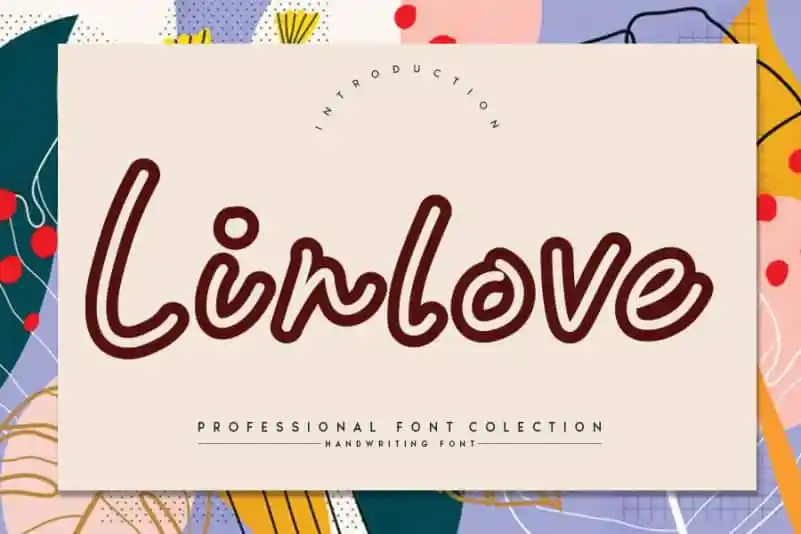
Linlove Display Font – Download Grátis
Linlove Display Font é uma elegante fonte escrita à mão que transborda vivacidade e originalidade. Seu arquétipo distinguido cria ambientes criativos, perfeitos para destacar seu trabalho especial. Sua personalização única e sua capacidade de trazer estilo inovador à qualquer projeto o tornam uma escolha irresistível para designers gráficos atentos. Desfrute da Linlove Display Font em cada página que você cria — ela certamente transformará a forma como vê seu trabalho.